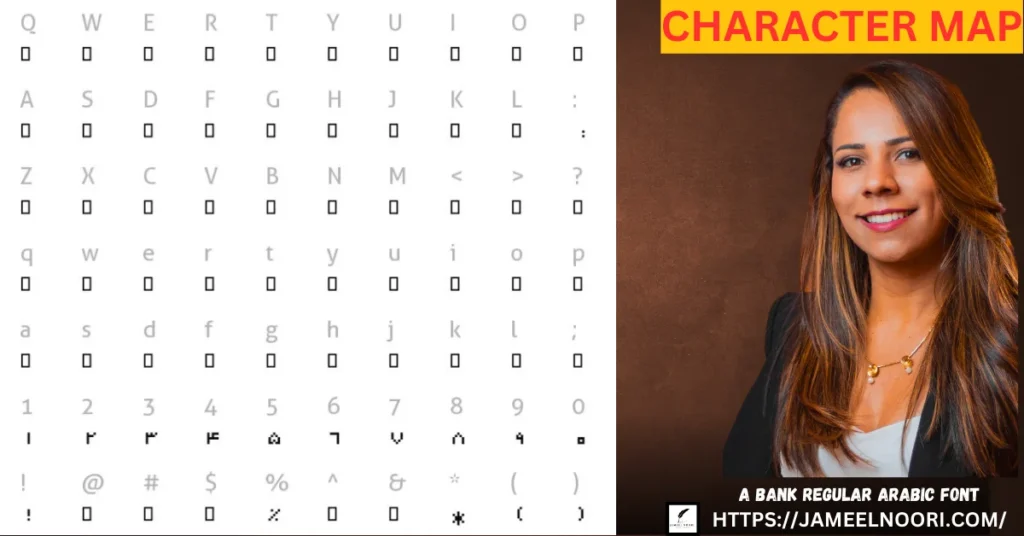
Key Features of A Bank Regular Arabic Font
- Clean & Smooth Characters: Har character properly designed aur readable hai.
- Multi-Language Support: Urdu fonts aur Arabic fonts ke saath compatible.
- Versatile Usage: Social media posts, banners, websites, print media me use ho sakta hai.
Why Choose A Bank Regular Arabic Font for Your Projects
A Bank Regular Arabic Font ka use karne ke bohat sare advantages hain:
- Elegant Calligraphy: Is font ki design modern aur readable hai.
- Professional Look: Business reports, brochures aur social media graphics me professional touch deta hai.
Tips to Use A Bank Regular TTF Arabic Font Effectively
- Use bold headings for emphasis.
- Maintain proper line spacing for readability.
- Combine with complementary Urdu fonts for attractive design.
- Avoid overusing the font to maintain professional appeal.
A Bank Regular Arabic Font designers aur content creators ke liye ek perfect solution hai jo Arabic fonts aur Urdu fonts dono me high-quality calligraphy aur readability provide karta hai. Is font ki popularity, 5-star user rating, aur 211,485 downloads ye sabit karte hain ke ye font Pakistan ke har designer aur student ke liye reliable choice hai. Chahe aap web design, print media, ya social media content create kar rahe hon, A Bank Regular TTF Arabic Font professional look aur elegant design ke liye ideal hai.
What is A Bank Regular Font?
A Bank Regular Arabic Font is a Regular TrueType font widely used for Arabic and Urdu typography projects.
What is the best way to combine it with other fonts?
Pair it with complementary Urdu or Arabic fonts for headings and body text to create a professional look.